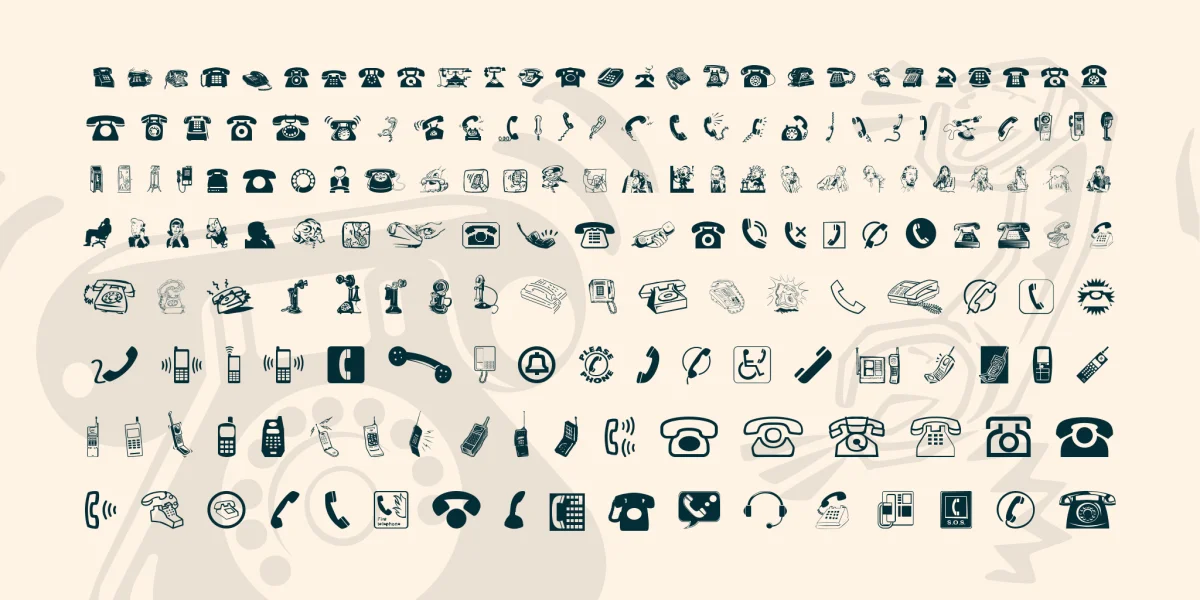
I AM TELEFONO es una gran colección de 173 teléfonos ordenados por tipos, estilo o forma. Muchas veces se necesita un bonito teléfono para rematar una pieza de diseño gráfico, con esta recopilación los tienes todos en un sólo archivo ttf.Thank you for your interest in my symbol font :) This font is free for personal use only.If you are interested in commercial use, you can buy the license in defharo.com/diseño-grafico/simbolos-telefono-art-vector/You may redistribute my fonts on your site as long as credit is defharo.com as the original author.Donations are always welcome :)